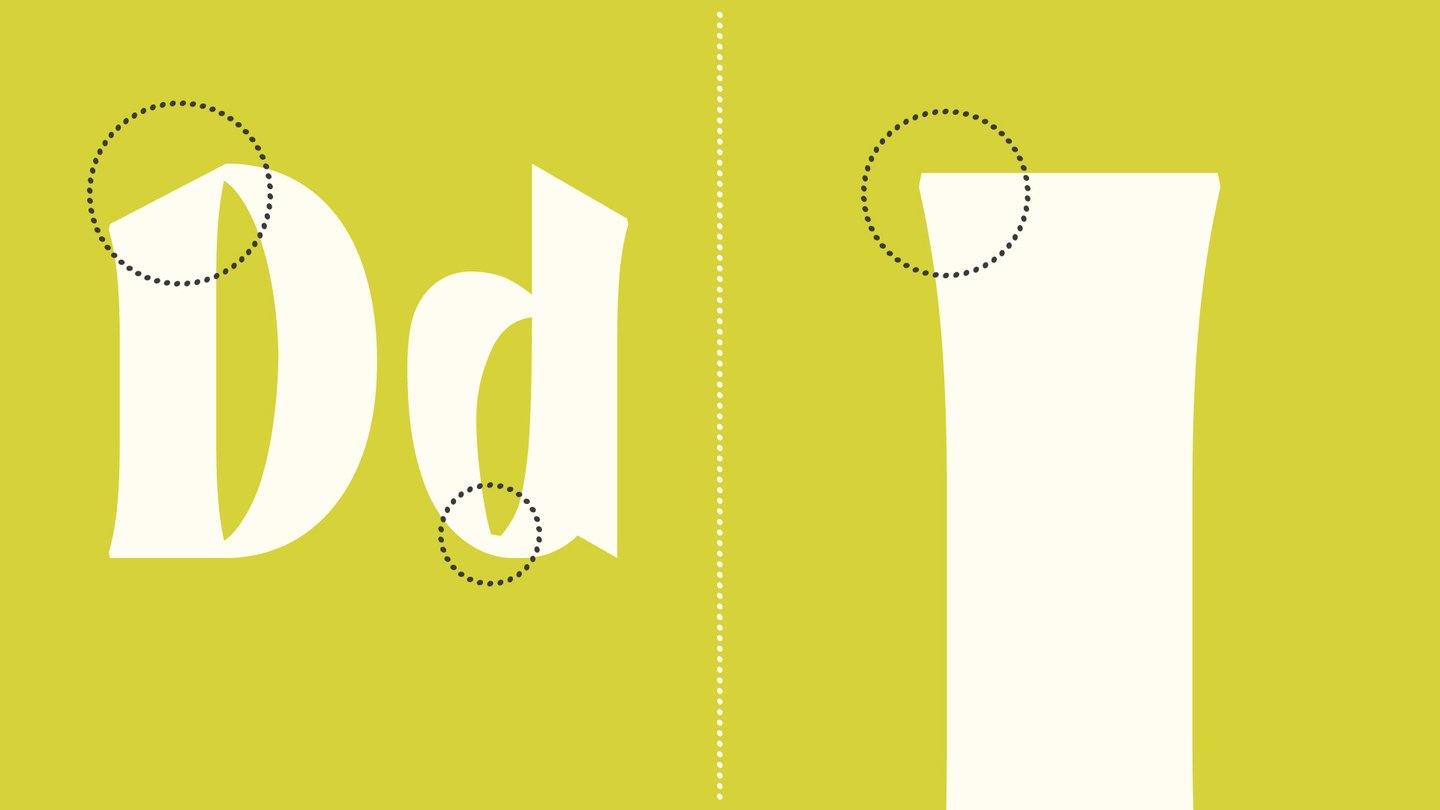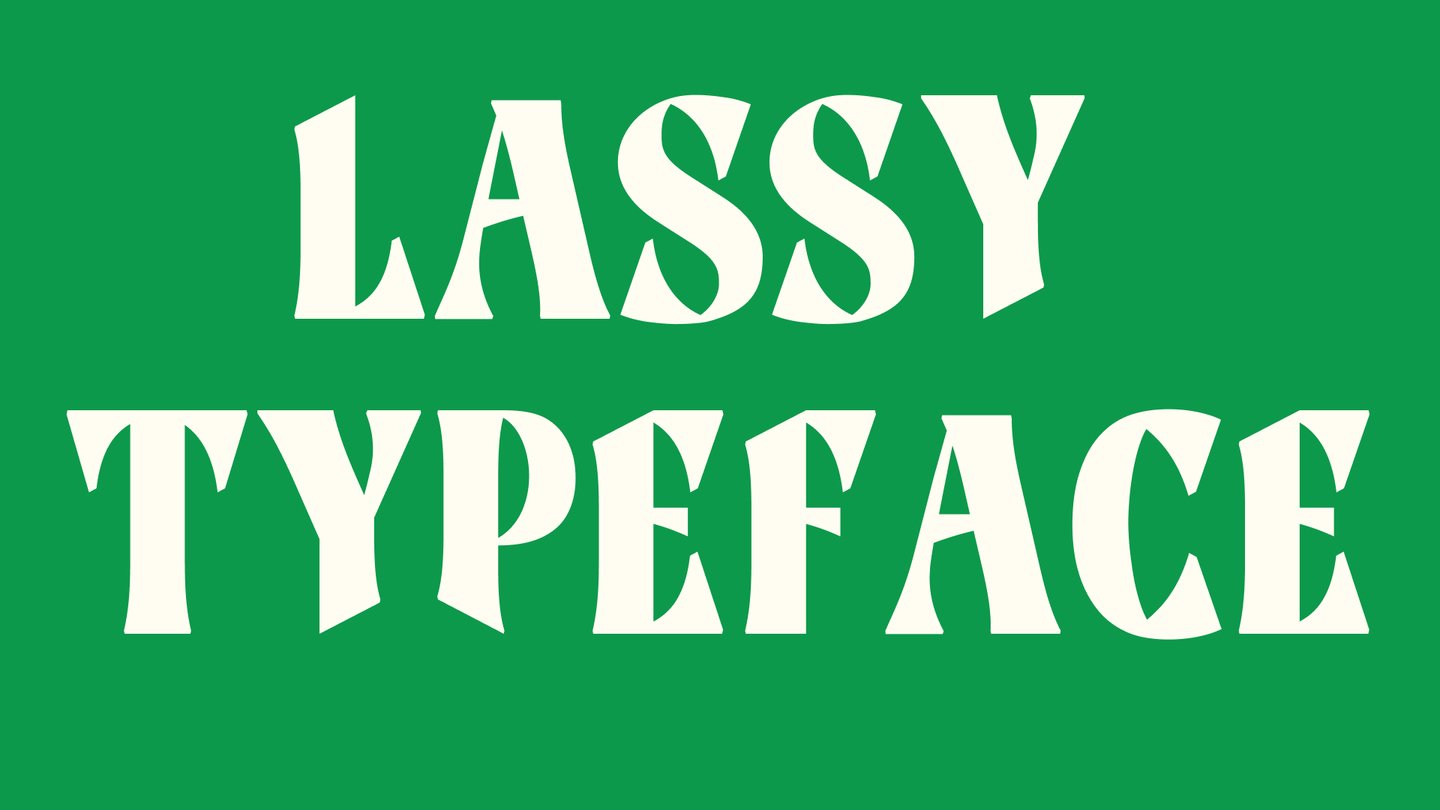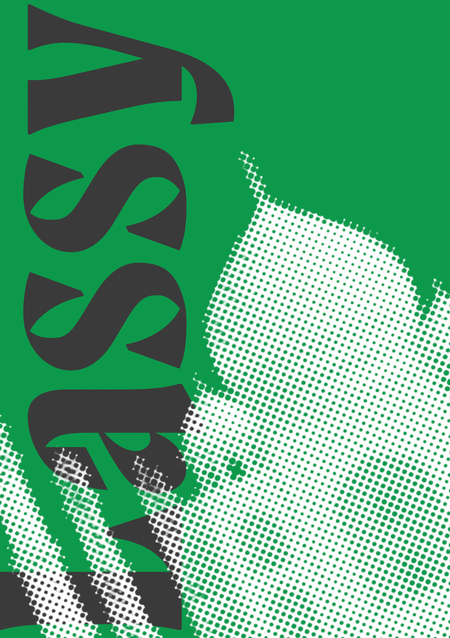
The Letters and the City
Для меня, как для дизайнера, Индия стала самым
запоминающимся культурным опытом в жизни.
Особенно поразило то, как в одном месте
в такой гармонии могут сосуществовать столько разных культур, религий и социальных классов.Это противоречие стало отправной точкой
в работе над всем проектом.
Lassi возник как визуальное впечатление от путешествия в Индию и наблюдения за локальным леттерингом: вывесками, надписями и типографикой в городской среде.
Куда бы вы ни поехали, это каким-то образом становится частью вас. — Анита Десаи